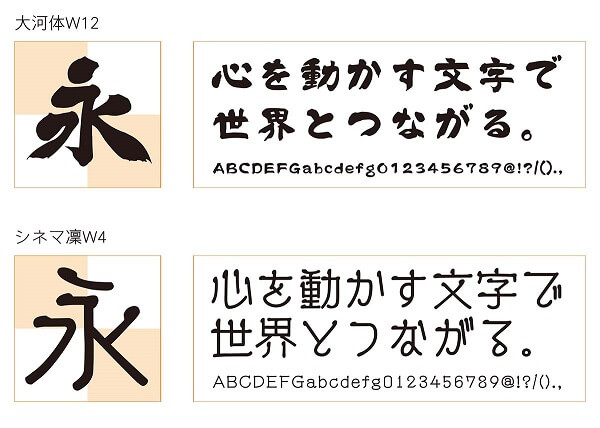
ダイナフォントDynaSmartの新しい書体「大河体W12」「シネマ凜W4」登場!
今回、日本語新書体「大河体W12」、「シネマ凜W4」を含む12書体を追加収録したそう。
大河体W12は、筆文字ならではの勢いや力強さを表現しつつ女性書道家らしい繊細さも感じさせる毛筆系書体。
昨年リリースとなった、字幕タイトルライターが字幕文字に自身の手書き文字の特徴を加味した書体「シネマ凜」に、今回W4の太さを追加。使用用途が広がりそうです。
そのほか、OpenType Std規格のJIS2004基準に応じたOpenType StdN規格の痩金体 StdN W3、徽宗宮 StdN W5、欧陽詢体 StdN W5、宗楷書 StdN W7。
プロユースのフォントユーザー向けに、Adobe-Japan1-6仕様に対応したJIS2004字形とJIS90字形の2種類の特太ゴシック体 Pro-6、極太ゴシック体 Pro-6、超極太ゴシック体 Pro-6などを追加収録。